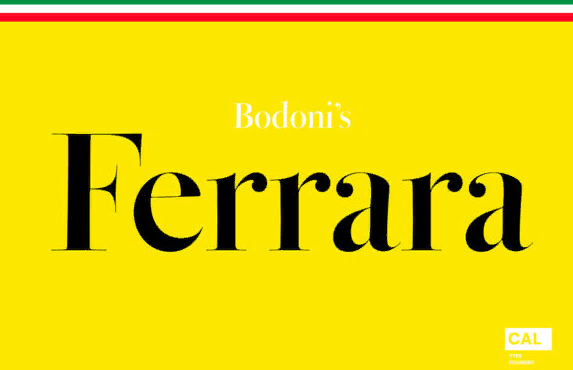
Название: Bodoni Ferrara Font (2021)
Bodoni Ferrara - это элегантный и аутентичный шрифт с засечками.
С его помощью можно воплотить в жизнь самые разные идеи, начиная от открыток, брендинга, этикеток и заканчивая многим другим.
Смело добавляйте его в свои любимые творения и позвольте себе поразиться полученному результату.